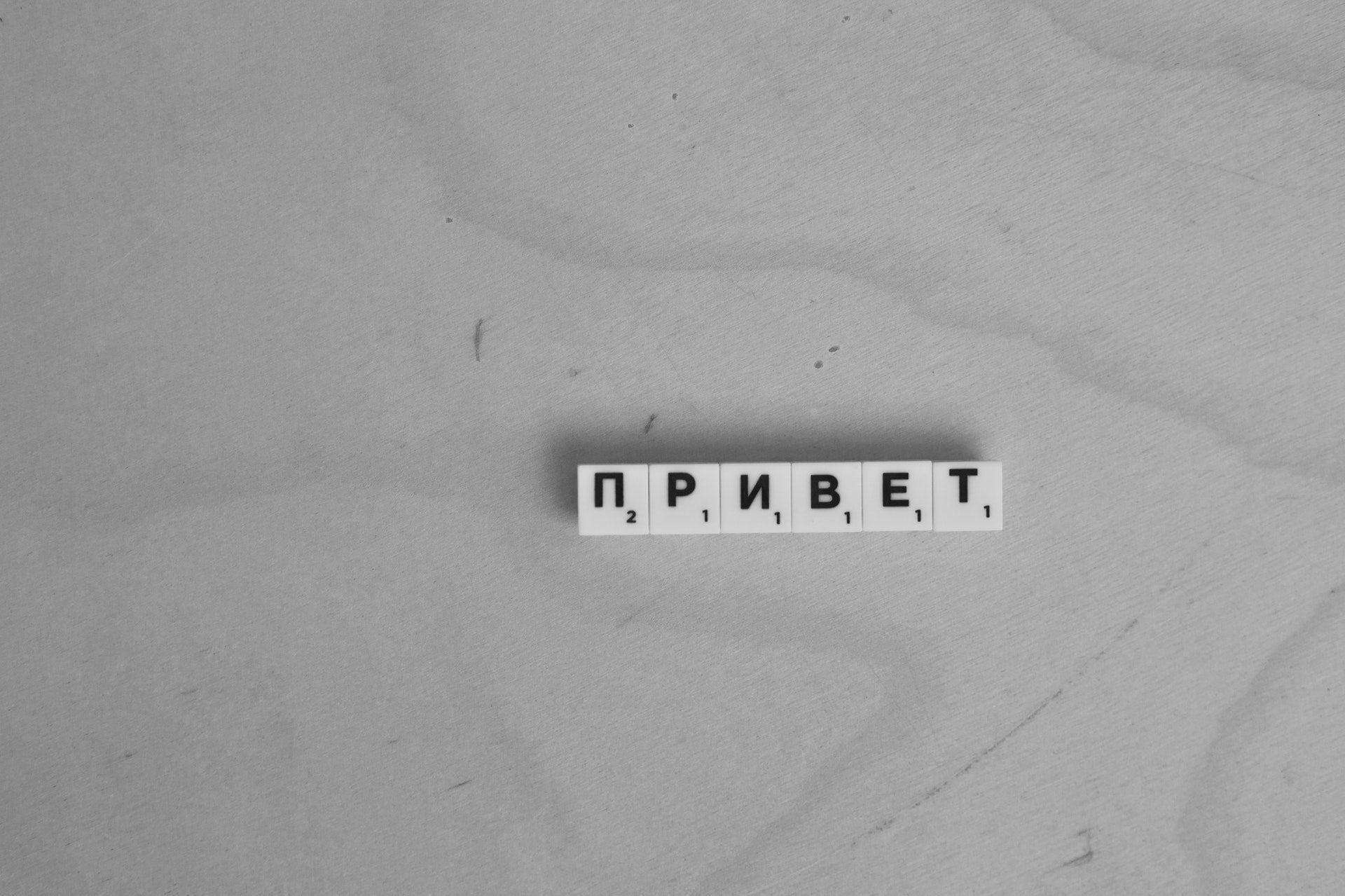
Шрифт — отличный инструмент, способный дополнить и украсить любой дизайн. А чтобы выбор был легким — мы подготовили подборку с лучшими кириллическими шрифтами, которыми можно пользоваться в Canva бесплатно.
Помните, что наши идеи и предложения по использованию — это только один вариант из множества возможных. Не ограничивайте свою фантазию, все кириллические шрифты из подборки имеют широкую область применения.
Эти кириллические шрифты бесплатно могут стать отличным дополнением дизайнов, связанных с творчеством, искусством и креативными проектами.
Легкий, будто весенний шрифт иллюстрирует движение кисточки с краской. Отлично подходит для открыток и любых ярких дизайнов.
Буквы этого шрифта будто пляшут, намекая на создание чего-то своими руками.
В этот кириллический шрифт внезапно ворвались буквы латинского алфавита. Такая надпись может украшать галерею современного искусства или модное арт-пространство. Главное, при использовании шрифта, убедиться, что иностранные буквы не путают читателя и он легко понимает, о чем идет речь.
Стилизация надписи маркером хорошо вписывается в макет, связанный с рисованием.
Аккуратные округлые засечки этого кириллица шрифта вызывают ассоциацию с каплями краски и делают его творческим и изящным.
Этот кистевой кириллический шрифт отлично подойдет к ярким, сочным дизайнам.
Книги, журналы, плакаты, листовки и упаковки — для любой печатной продукции важно выбрать подходящий кириллический шрифт. Он должен быть легко читаем и при этом созвучен стилю продукта. Смотрим, какие есть варианты.
Шрифт с близко расположенными друг к другу, аккуратными буквами будто несет в себе едва уловимое волшебство и атмосферу сказки. Так, например, он может украсить обложку книги.
Этот кириллица шрифт вдохновляет, его линии напоминают волны. Все, кто любят блокноты и ежедневники получат эстетическое удовольствие от продукта с такой надписью.
Пример открытки с уверенной надписью — такой, которая призвана мотивировать и настраивать на победу. Используйте настроение этого шрифта в своих дизайнах.
Хорошо читаемый шрифт с изюминкой в виде интересных линий буквы «а». Идеален для плакатов, визиток и другой полиграфии.
Этот мягкий кириллический шрифт вызывает ассоциации с лучшими книгами из детства.
Этот уверенный и яркий шрифт можно размещать на постерах, афишах и плакатах. А вишенка на торте — креативные элементы в написании нескольких букв, в том числе «М». Здорово смотрится в случае надписи со словом «Москва» и перекликается с логотипом «Метрополитена».
А это кириллические шрифты бесплатно способны сделать любой дизайн нежным, изящным и романтичным.
Оформляйте любовное послание с использованием этого шрифта — и точно не прогадаете.
Так может выглядеть строчка из песни или стихотворения...В паре с подходящей картиной этот шрифт может добавлять в дизайн романтику и легкость.
Используйте этот шрифт для коротких фрагментов текста, которыми вы хотели бы рассказать о чем-то элегантном.
Линии этого декоративного ретро шрифта изогнуты так, что напоминают изящный музыкальный инструмент. Макет с подобной надписью будет гармонично смотреться в музыкальном магазине или концертом зале.
Этот душевный шрифт создан по мотивам книг советского периода с 1960 по 1970 год. Его хочется использовать в случае вежливых, добрых надписей.
Это динамичный курсивный шрифт, в котором резкость и скорость письма гармонично сочетаются с изящной серьезностью. Шрифт позволяет имитировать быстрые надписи, сделанные вручную, сохраняя при этом элегантность и стиль.
Кириллица шрифт, который передает настроение романтики и детства одновременно. В мягких и озорных линиях шрифта будто спрятались трогательные эмоции.
Этот шрифт написан небрежными сухими мазками каллиграфического пера. Добавит очарование брендингу, упаковке продуктов, плакатам, приглашениям и открыткам.
Этот легкий шрифт написан школьными ретро-буквами. Отлично подходит для логотипов, цитат, заголовков и многого другого.
Используйте этот кириллица шрифт, чтобы сделать свой дизайн элегантным и романтичным.
Этот кириллический шрифт с элементами винтажной классики подойдет для многих трогательных и изящных дизайнов.
Шрифт с игривым названием «Ромочка» будто написан чернилами. Линии в некоторых буквах прерываются, в других — несимметричны. Используйте его, чтобы внести в дизайн легкое творческое настроение.